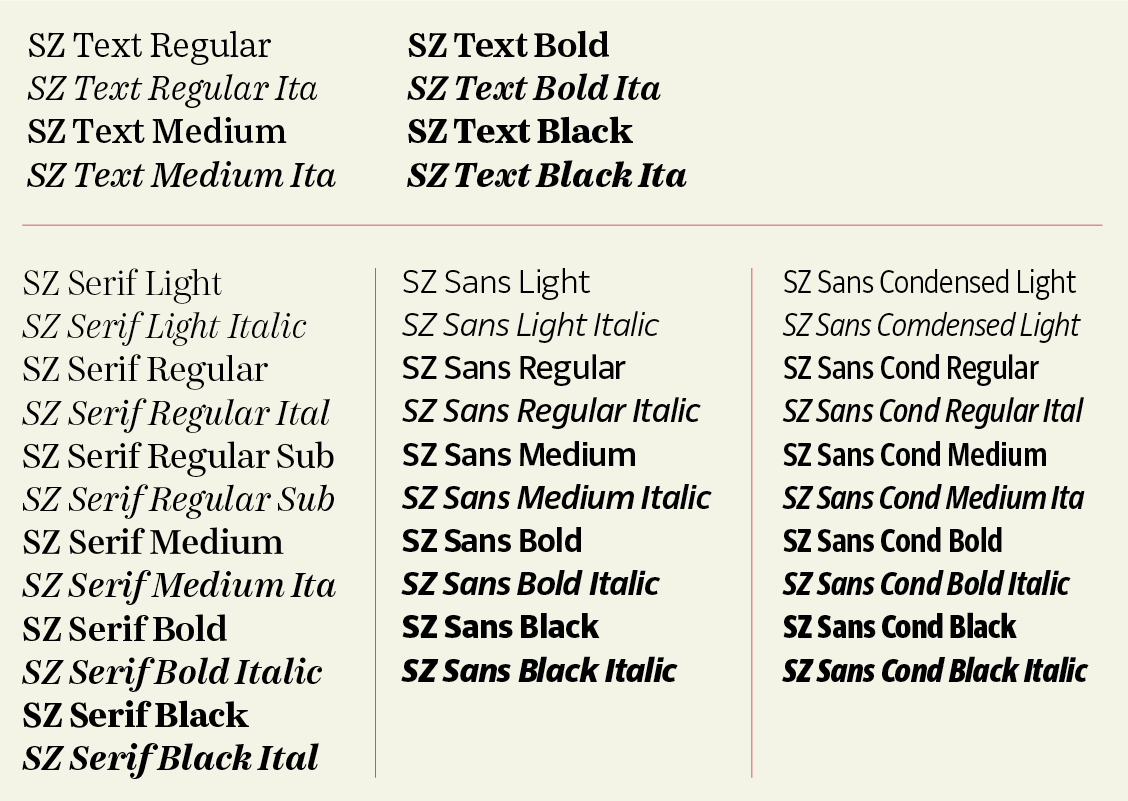
Ein Gespräch mit dem Schriftentwerfer Henning Skibbe über die neue Typografie der Süddeutschen Zeitung, Allerweltsschriften, die ›heilige Helvetica‹ und gekündigte Abos
Am Montag den 9. Juli 2012 erschien die Süddeutsche Zeitung mit renovierter Typografie, einschließlich neuer Exklusivschriften (Fontblog berichtete). Das Echo war neutral, ein bisschen Kritik, ein bisschen Lob. Ist das jetzt ein gutes Zeichen oder ein schlechtes? Wir sprachen mit dem Entwerfer der SZ-Schriftfamilie, den Hamburger Designer Henning Skibbe.
Fontblog: Vor 50 Tagen ging die Süddeutsche Zeitung mit neuem Layout und neuen Schriften in den Druck, entworfen vom Bureau ErlerSkibbeTönsmann. Wie lautet heute das Resümee?
Henning Skibbe: Das Feedback der Leser war wie zu erwarten gemischt. Es gab ablehnende, teils korrigierende Meldungen (z. B. waren die Schriften im Kreuzworträtsel und Börsenteil zu klein), teils positive Meldungen. An den Problemen wurde und wird gearbeitet. Überraschenderweise waren ein Drittel der Leserbriefe positiv. Das sehen wir und die SZ nicht als selbstverständlich an. Positive Kritik wird ja oft nur durch ein anerkennendes Kopfnicken ausgedrückt. Aber wenn jemand einen langen Brief oder eine Mail schreibt, dann muss es wohl ernst gemeint sein. Das bestätigt uns natürlich, vor allem da die gute Lesbarkeit der Schriften vielfach betont wurde.
Nicht zuletzt ist auch interessant, das bis letzte Woche weniger als 20 Abonnenten gekündigt hatten. Dies zeigt, dass unser Weg der behutsamen Reform der richtige für den Leser und die Zeitung ist.
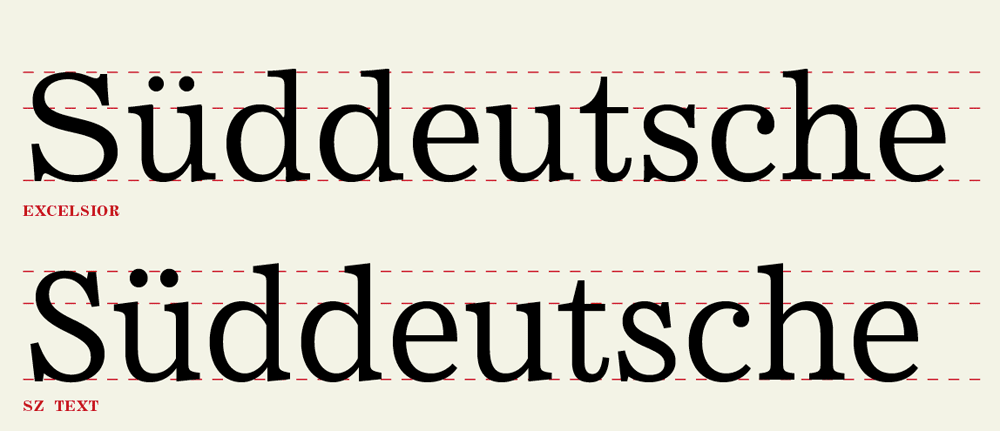
F: Fast 50 Jahre wurde – neben anderen Schriften – die Helvetica bei der SZ verwendet? Wir reagierte die Leserschaft auf deren Entsorgung?
HS: Da gab es überraschenderweise gar keine großen Reaktionen. Designer sehen das vielleicht etwas anders. Für Typografen ist die Helvetica ein Heiligtum. Doch wenn man die Wahrnehmung der Leser prüft – und diese sind zum Großteil keine Gestalter –, dann wird Helvetica mit Arial gleichgesetzt. Der Unterschied ist für Laienaugen kaum wahrnehmbar. Leider. Und damit entzaubert sich die Helvetica recht schnell.
1965 als die Helvetica bei der SZ Einzug hielt, war das anders. Da gab es weder Windows, noch Arial. Die Frage ist dann nach 5 Jahrzehnten, ob eine führende Tageszeitung es sich leisten kann, mit einer »versehentlichen Allerweltsschrift« Schlagzeilen zu machen. Aus solchen und ähnlichen Gründen haben sich auch andere Marken und Medien in den letzten Jahren von Helvetica & Co verabschiedet.
F: Wie verlief der Weg von der Textschrift Excelsior zur neuen SZ Text?
HS: Das Briefing für die Textschrift war klar und unmissverständlich. Die SZ erklärte uns, dass man das Schriftbild und dessen warmen und runden Charakter nicht in Frage stellen wolle. Aber die Schwächen wurden in den letzten Jahren unübersehbar. Der gesamte Prozess wurde als Reform und nicht als Revolution angelegt. Dies definierte den gestalterischen Spielraum für die Textschrift.
F: Gestalterischer Spielraum … geht es etwas konkreter?
HS: Eine wichtige erste Erkenntnis war für uns, dass der Kontrast und damit der Grauwert der SZ Text mit der Excelsior vergleichbar bleiben müsse. Der Kontrast und der daraus resultierende Grauwert ist bei Lesegrößen das entscheidende (unbewusste) Merkmal einer Schrift. Ob Serifen oder Kurven dann so oder anders geformt werden, ist bei Textgrößen dann schon beinahe egal. Dies gilt natürlich nur, wenn man prinzipiell ähnliche Schriften miteinander vergleicht.
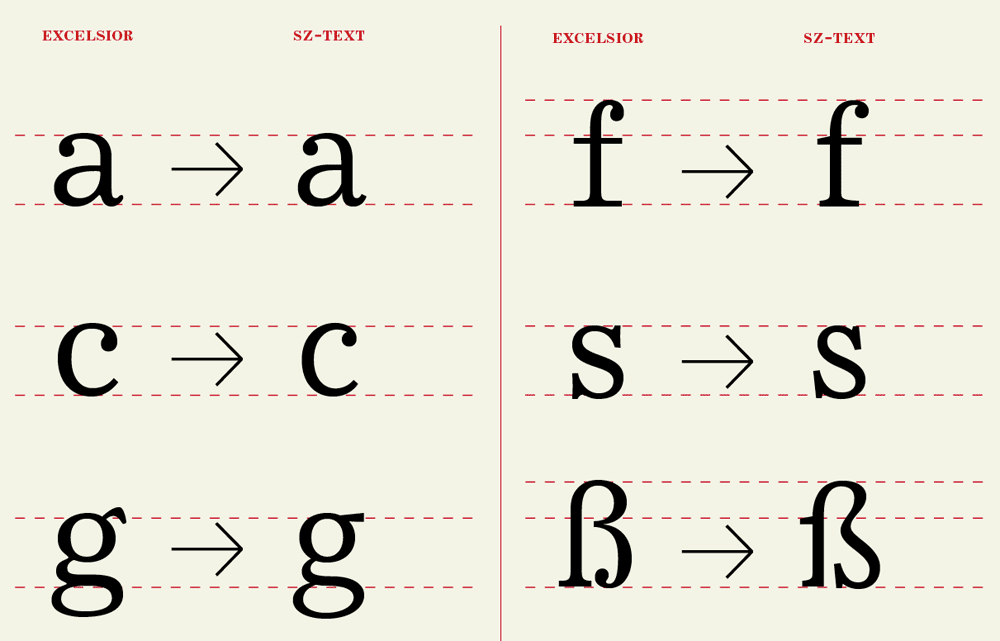
F: Welches waren der die Schwächen der alten Lesetypografie?
HS: Wir haben die Excelsior analysiert und überlegt, an welchen Punkten man ansetzen müsse, damit die neue SZ Text besser lesbar, effizienter und das Schriftbild ruhiger sein sollen. Beispielsweise sind die Kurven der SZ Text an die Stämme angesetzt, so dass offenere Innenräume entstehen. Das wiederum erlaubte es uns diesen gewonnenen Innenraum bei der Buchstabenbreite zu subtrahieren. Die SZ-Text hat zudem weniger ausladende Versalien und Serifen als die Excelsior.
Und nicht zuletzt haben wir jedem Buchstaben eine zeitgemäßere Form gegeben, immer mit dem Gedanken im Hinterkopf, dass es eine serifenlose Headlineversion der Schrift geben würde. Der Excelsior sieht man ihre Vergangenheit als Bleisatzschrift deutlich an. Das mögen die einen als Charme bezeichnen, doch sind die daraus resultierenden Formen und Kurven nicht nur eine Reminiszenz an längst vergangene Zeiten sondern schwächend die Lesbarkeit.
F: Erik Spiekermann ist die neue SZ-Typografie nicht mutig genug, zu kontrastlos, zu grau. Durftet ihr nicht mehr wagen, oder wolltet ihr nicht?
HS: Beides. Die großen Relaunches der letzten Jahre auf dem deutschen Zeitungsmarkt haben zwar mutige gut gestaltete Blätter hervorgebracht, aber dabei auch einen guten Teil der alten Leser und Abonnenten verschreckt. In Zeiten von generell rückläufigen Verkäufen am Kiosk und bei Abos, wollte die SZ es nicht riskieren, durch drastische Maßnahmen einen Teil der Leser zu verschrecken. Das mag vielleicht ängstlich klingen, aber ein verlorener Leser bzw. Abonnent kommt erfahrungsgemäß nicht mehr zurück. Hinzu kommt das Profil der SZ-Leser. Ein Gutteil der SZ-Leser kann durchaus als konservativ bezeichnet werden. Sie lesen das Blatt oft seit Jahrzehnten und empfinden per se jede Änderung an der Zeitung als Affront. Nachdem sich die SZ zig Jahre visuell kaum gewandelt hat, kann man nicht mit einem Schwung alles ändern. Da ginge zu viel vom optischen Markenkern verloren.
schade, dass das weichspülen von charakter als »zeitgemäß« verkauft wird. wenn die süddeutsche jetzt den inhalt anpaßt, bestelle ich das abo auch ab.